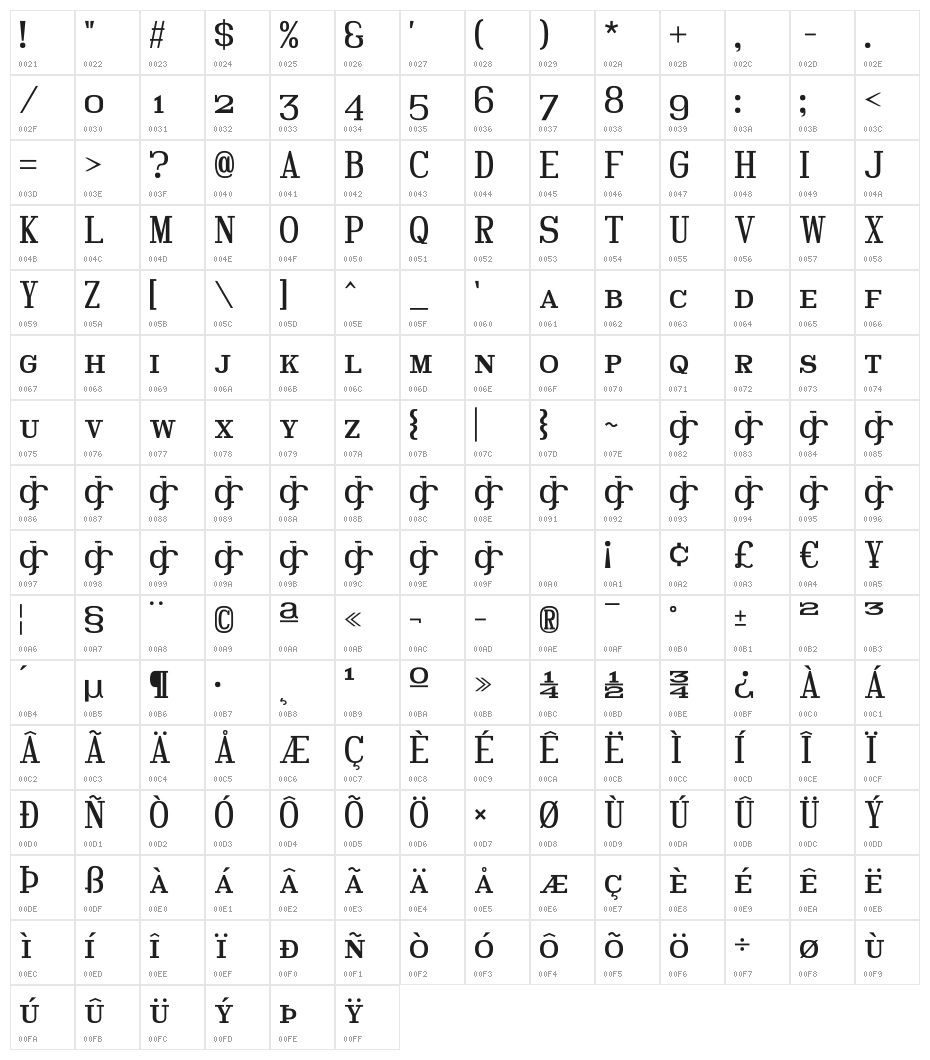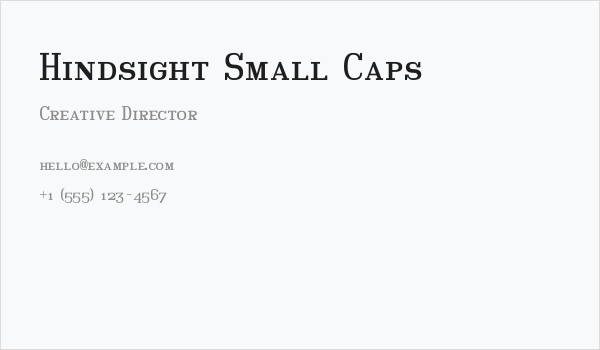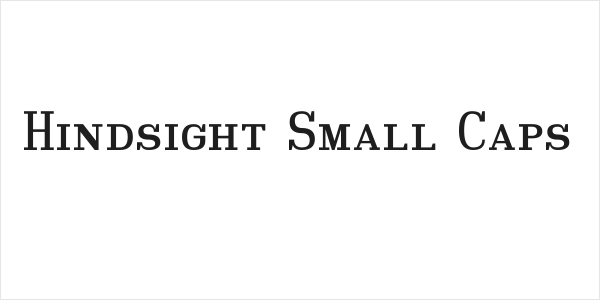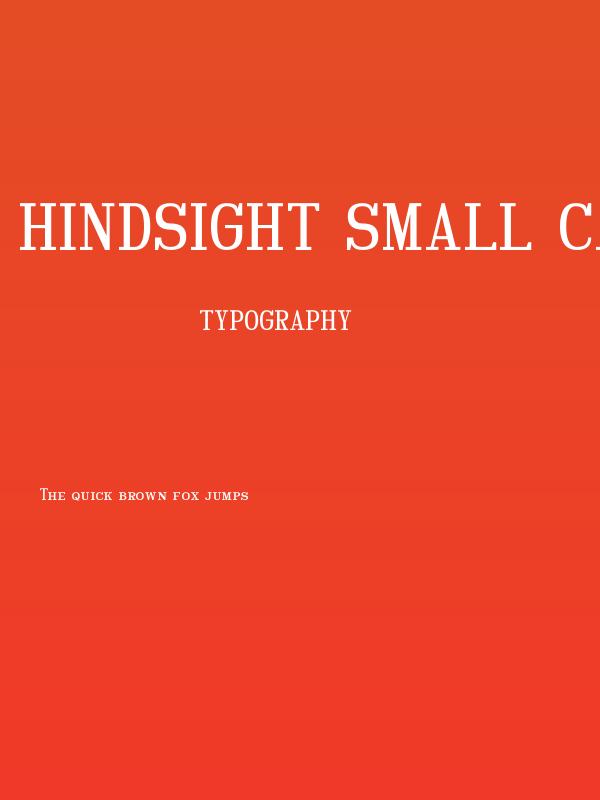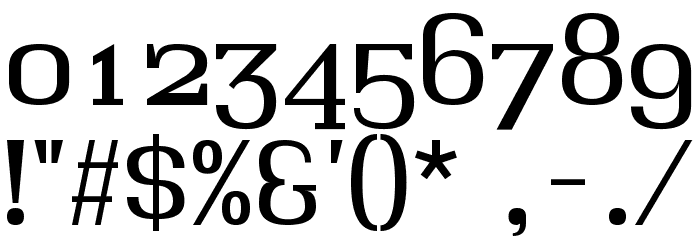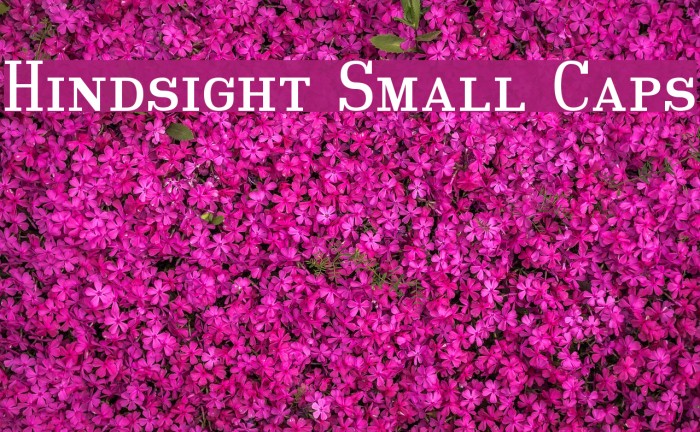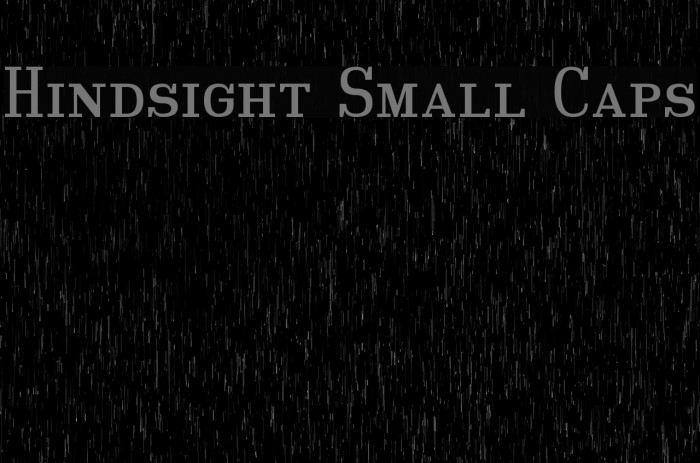
Hindsight Small Caps Font
Fonts by dartcanada.tripod.com - Darren Rigby
| Catégories | Serif |
| Style général | Classic |
| Cas d'utilisation | Headlines, Logos, Editorial Design |
| Projets proposés | Ideal for use in editorial design, book covers, formal invitations, branding for luxury products, and corporate identity materials. |